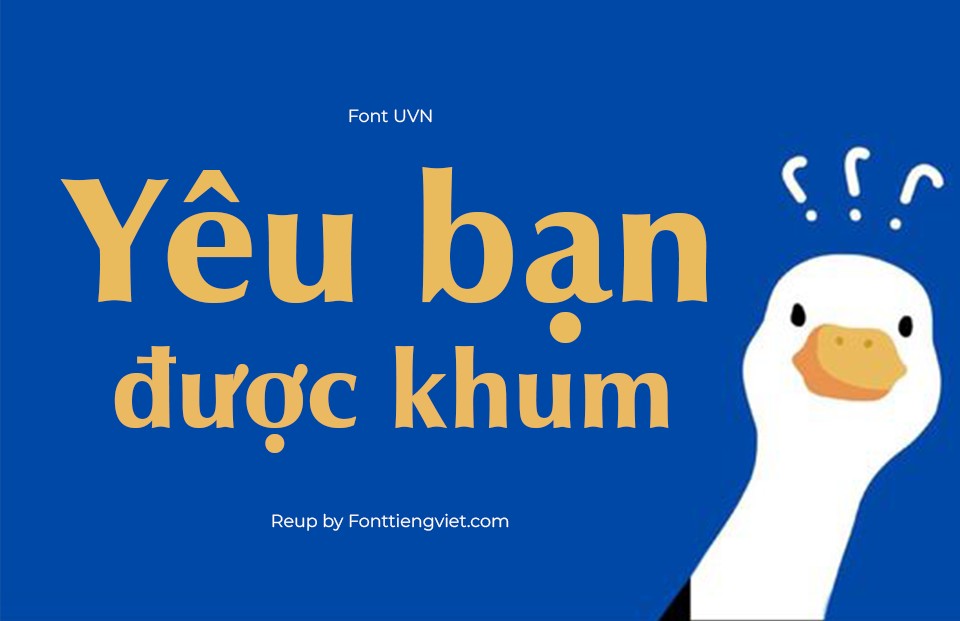
Giới thiệu về Font Việt Hóa UVN Nhan Nang
Trong lĩnh vực thiết kế đồ họa và soạn thảo văn bản tại Việt Nam, việc lựa chọn một bộ Font Chữ phù hợp đóng vai trò quan trọng trong việc truyền tải nội dung. Font Việt Hóa UVN Nhan Nang là một trong những kiểu chữ thuộc bộ mã UVN nổi tiếng, được thiết kế tối ưu cho mục đích trình bày văn bản chuyên nghiệp. Với đặc điểm nét chữ rõ ràng và cân đối, bộ font này giúp người dùng dễ dàng tạo ra những ấn phẩm truyền thông hoặc tài liệu học tập có tính thẩm mỹ cao mà vẫn đảm bảo sự trang trọng cần thiết.
Đặc điểm nổi bật của Font Việt Hóa UVN Nhan Nang
Thiết kế tối ưu cho tiếng Việt
Ưu điểm lớn nhất của Font Việt Hóa UVN Nhan Nang chính là khả năng hiển thị tiếng Việt hoàn hảo, không xảy ra lỗi dấu hay khoảng cách chữ. Kiểu dáng chữ được tinh chỉnh để phù hợp với các tiêu chuẩn trình bày hiện đại, giúp văn bản trở nên dễ đọc và bắt mắt hơn. Đây là sự lựa chọn lý tưởng cho các bạn học sinh, sinh viên và giáo viên khi cần thiết kế slide bài giảng hoặc làm báo cáo học thuật định kỳ.
Tính ứng dụng linh hoạt trong đời sống
Không chỉ dừng lại ở các văn bản hành chính, Font Việt Hóa UVN Nhan Nang còn được ứng dụng rộng rãi trong việc làm thiệp mời, tiêu đề báo tường hay các banner tuyên truyền tại nhà trường. Nét chữ vững chãi của nó tạo cảm giác tin cậy và truyền cảm hứng mạnh mẽ cho người xem, giúp thông điệp được lan tỏa hiệu quả hơn trong môi trường giáo dục.
Kết luận và hướng dẫn sử dụng